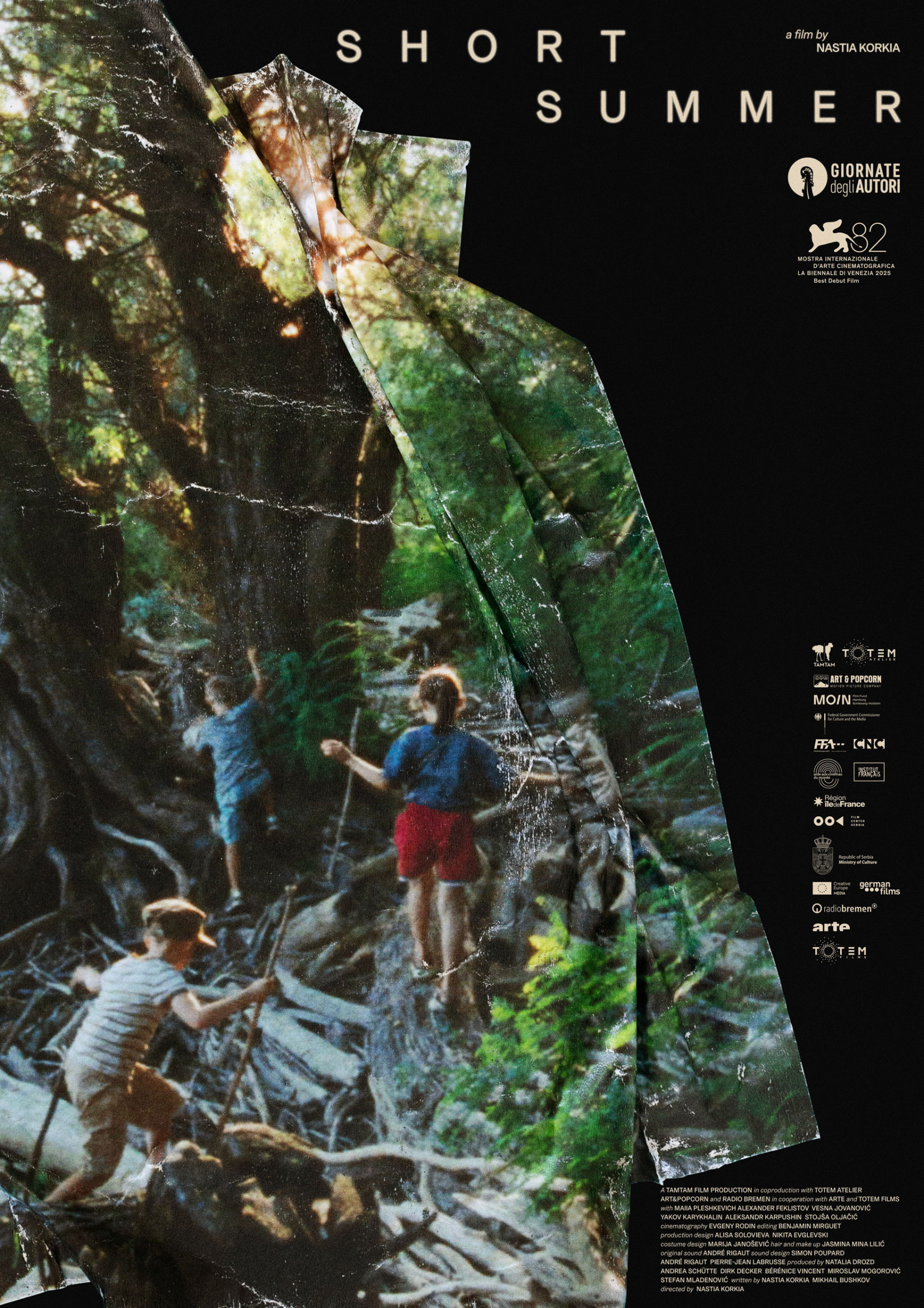
Short Summer
Short Summer ist ein Spielfilm von Nastia Korkia.
Das Still zeigt drei spielende Kinder in einer sonnigen Landschaft, welches gewaltsam an den Rand des Bildes gedrängt wird. Es gibt den Blick frei auf eine darunter liegende Dunkelheit, die die unterschwellige Bedrohung im FIlm symbolisiert. Der sporadische Einsatz von Schrift spielt auf die Art und Weise an, wie sich die Kamera im Film durch die Umgebung bewegt.